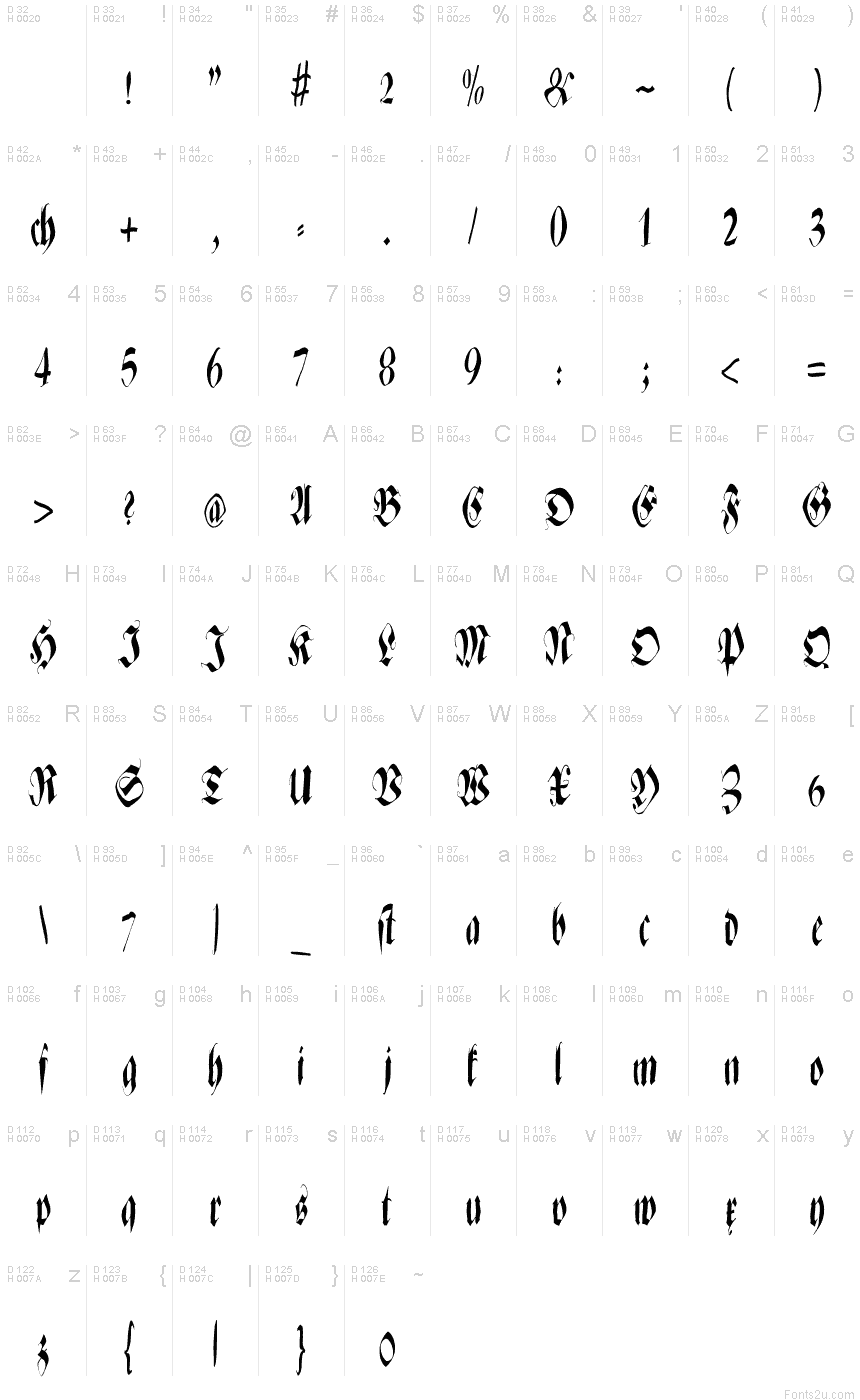
ZenFraxFreestyleCondensed
ZenFrax Freestyle Condensed autorstwa M. Kleina to bezpłatny, średniowieczny gotycki krój pisma o ostrym, kaligraficznym charakterze. Litery czerpią z dramatyzmu czcionek blackletter – mają ostre kąty, dzielone pociągnięcia i kręcone ozdobniki – ale ogólny klimat jest żywy, a nie surowy, dzięki wąskiemu rytmowi, który nadaje teksturze dynamiki.
Świetnie sprawdza się w nagłówkach plakatów, okładkach albumów, książkach fantasy, ulotkach eventowych oraz w brandingu browarów czy tawern, gdzie potrzebny jest historyczny klimat z charakterem. Jako darmowy font idealnie nadaje się też do krótkich tytułów, napisów i monogramów, ponieważ jej haczykowate krzywizny i kolczaste łączenia robią wrażenie już przy kilku znakach.